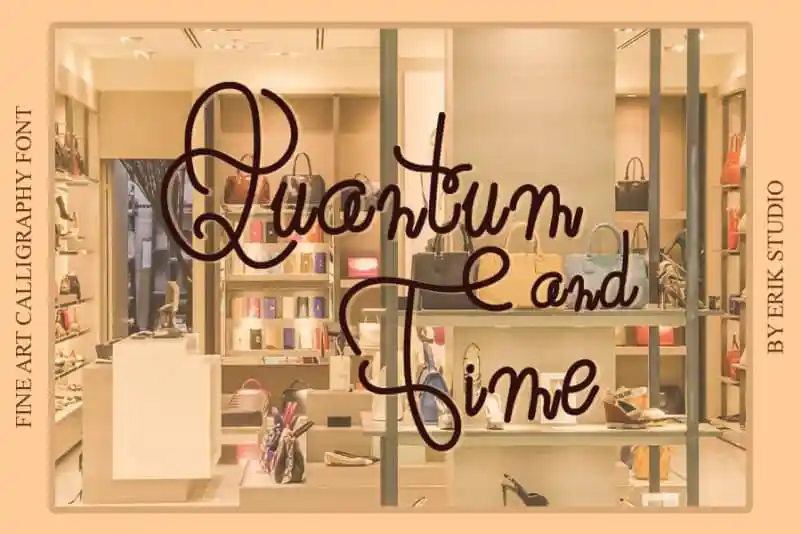
Quantum And Time Script Font – Download Grátis
Quantum And Time Script Font é uma linda tipografia romântica e suave, inspirada no estilo das cartas manuscritas. Seus caracteres dançam sobre a linha base, oferecendo um toque elegante e alegre que fazem deste tipo de fonte perfeito para escrever convites de casamento, cartões ou qualquer design que precise de uma pitada romântica e personalizada. Suave e encantadora, esta fonte certamente enriquecerá seu trabalho gráfico. Perfeita para criar um tom delicado e apaixonado nas suas criações digitais. Escolha Quantum And Time Script Font se desejar adicionar uma pitada romântica e única a qualquer projeto que precise de um toque especial.